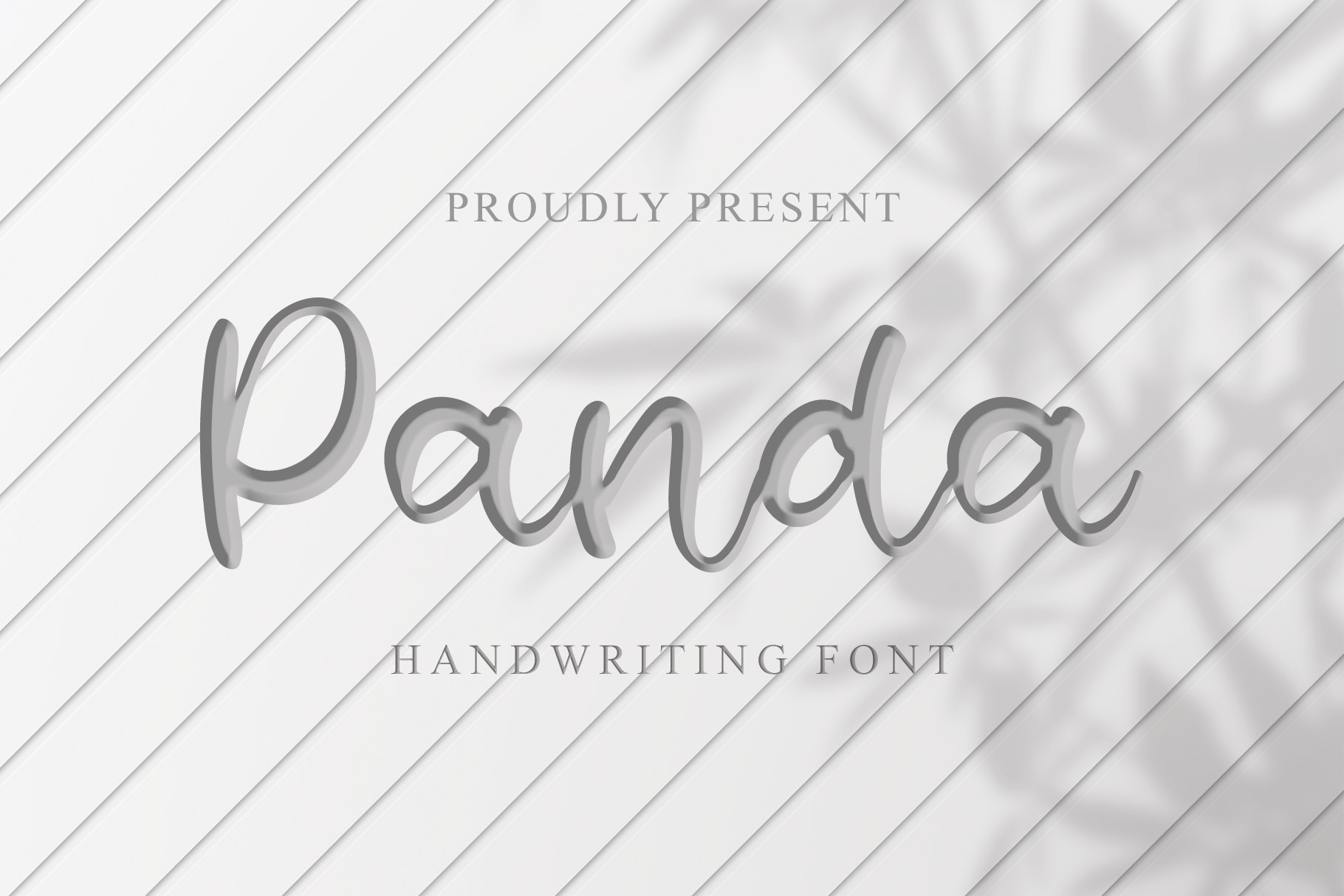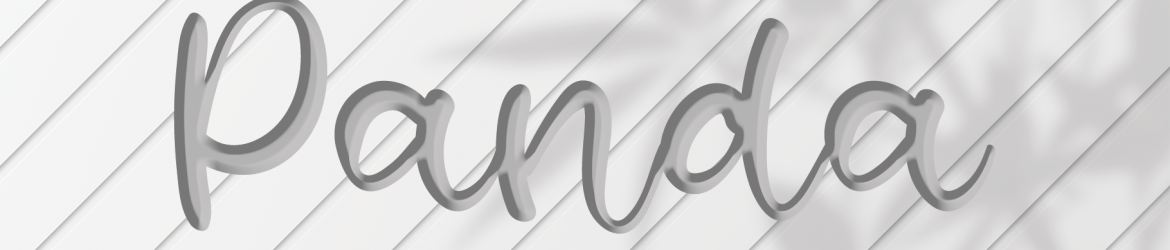
Panda Font – Download Grátis
A font Panda é perfeita para quem valoriza estilo moderno combinado com detalhes cuidadosamente elaborados. Ela é uma tipografia escrita à mão redonda, ideal para adicionar um toque de elegância a qualquer projeto. Esta font tem o potencial de tornar-se um valioso membro da sua biblioteca personalizada, pois está equipada para criar trabalhos que destacam em diversos temas. Seja ela usada em cartazes publicitários, flyers ou até mesmo em design gráfico digital, a Panda garante sempre uma aparição arredondada e impecável nas suas criações. É como se você trouxesse um pedacinho da natureza para o seu projeto, uma vez que sua letra redonda é perfeitamente adaptada para dar vida à sua ideia de forma criativa e sofisticada. Seja você designer gráfico ou web, essa font oferece a liberdade de criar com autenticidade e estilo único.